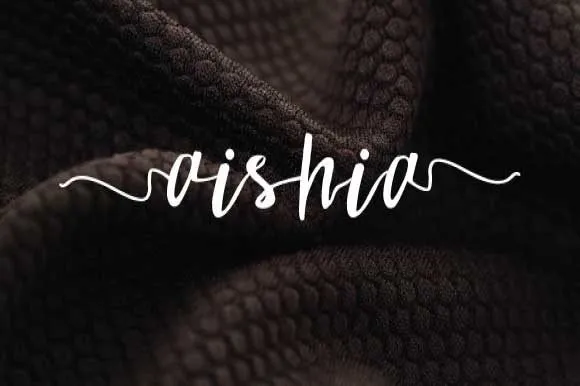
Aishia Script Font – Download Grátis
Esta é uma fonte script que se destaca pela sua facilidade de uso e beleza natural. Ela tem um aspecto feminino aparentemente simples, mas com a coragem necessária para capturar o coração do consumidor. Este design foi criado por Daikian, designer atrás da criação desta fonte elegante e suave. Aishia Font é uma escolha perfeita não só para logos e cartões de presentes, mas também para embalagens, roupas, materiais promocionais como flyers e lacre. Ela complementará sua identidade visual de maneira única, tornando seu design inegavelmente irresistível. A fonte é perfeita para qualquer aplicação em que deseje destacar seu trabalho ou produto. Esta font é especialmente adequada para ambientes criativos onde o formato deve ser lúcido e agradável aos olhos. Seja você um designer gráfico, editor de imagens ou alguém que simplesmente gosta de criar design pessoal, Aishia Font não apenas complementará seu trabalho, mas poderá ajudá-lo a tornar qualquer projeto em destaque, seja para eventos sociais, produtos em linha ou materiais de marketing.